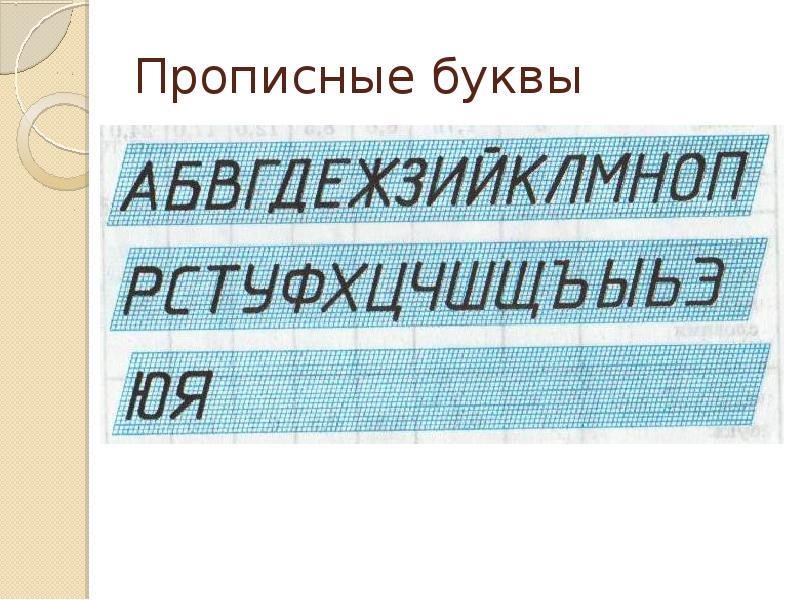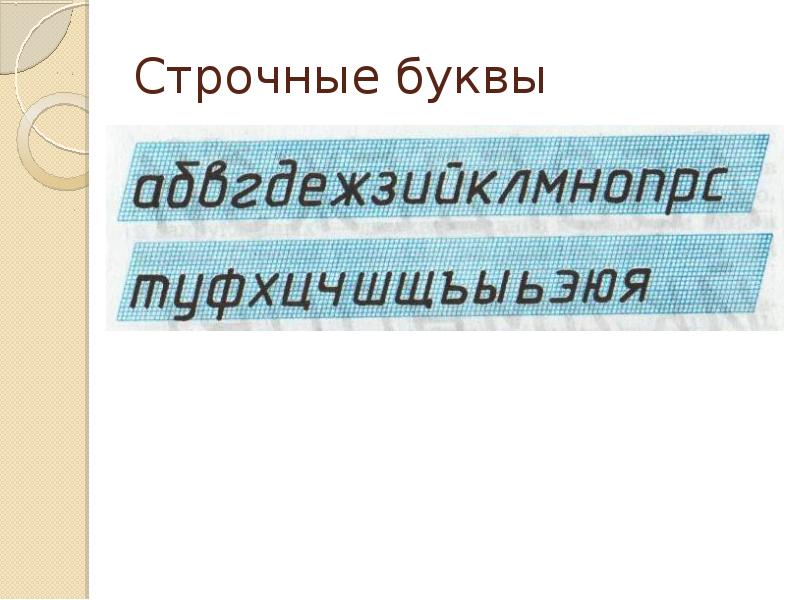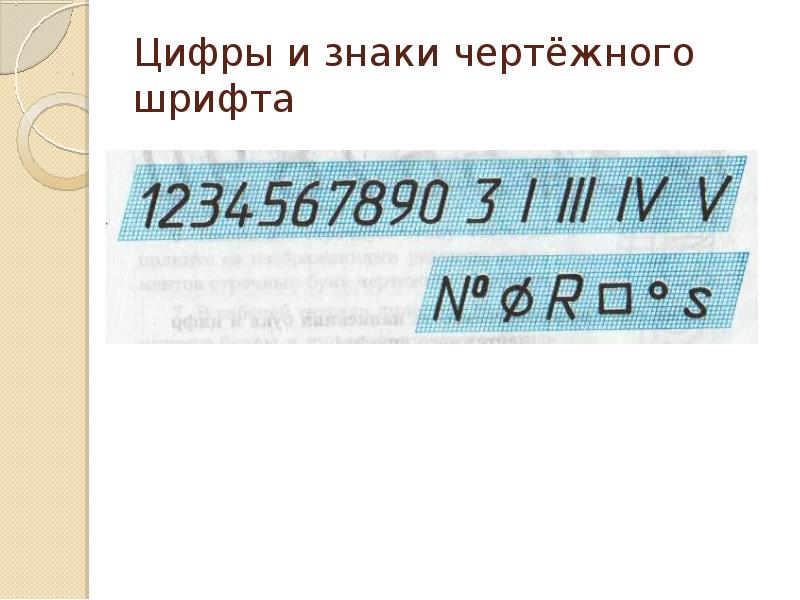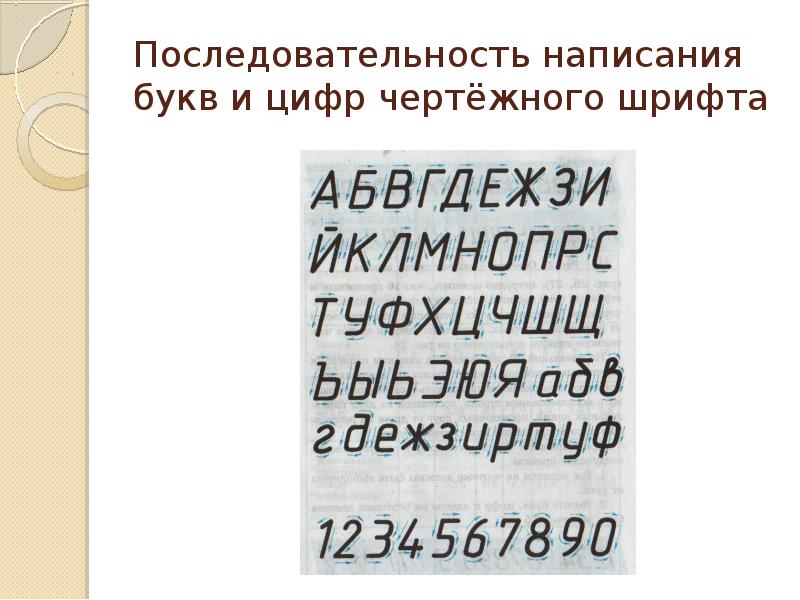
Шрифт чертёжный Слепнев Н.И. 2017 год
Размеры шрифта За размер шрифта принимается величина, определяющая высоту прописной (заглавной) буквы; Стандарт устанавливает десять размеров шрифта:...
Размеры шрифта За размер шрифта принимается величина, определяющая высоту прописной (заглавной) буквы; Стандарт устанавливает десять размеров шрифта: 1,8; 2,5; 3,5; 5; 7; 10; 14; 20; 28; 40.
Прописные буквы Высота прописной (заглавной) буквы (h) равна размеру шрифта; Нижние элементы букв Д, Ц, Щ и верхний элемент буквы Й выполняются за...
Прописные буквы Высота прописной (заглавной) буквы (h) равна размеру шрифта; Нижние элементы букв Д, Ц, Щ и верхний элемент буквы Й выполняются за счёт расстояний между строками; Толщина линий шрифта (d) равна 0,1h; Ширина большинства прописных букв равна 0,6h или 6d; Ширина букв А, Д, М, Х, Ц, Ы, Ю равна 0,7d; Ширина букв Ж, Ф, Щ, Ш, Ъ равна 0,8d; Ширина букв Г, З, С равна 0,5d;
Прописные буквы
Строчные буквы Высота большинства строчных букв (с) равна 0,7h; Верхние и нижние элементы строчных букв выполняются за счёт расстояний между строками...
Строчные буквы Высота большинства строчных букв (с) равна 0,7h; Верхние и нижние элементы строчных букв выполняются за счёт расстояний между строками и выходят на величину 3d; Ширина большинства сточных букв равна 5d; Ширина букв а, м, ц, ъ равна 6d; Ширина букв ж, т, ф, ш, щ, ы, ю равна 7d; Ширина букв з, с равна 4d.
Строчные буквы
Расчёты параметров чертёжных шрифтов
Цифры и знаки чертёжного шрифта
Последовательность написания букв и цифр чертёжного шрифта